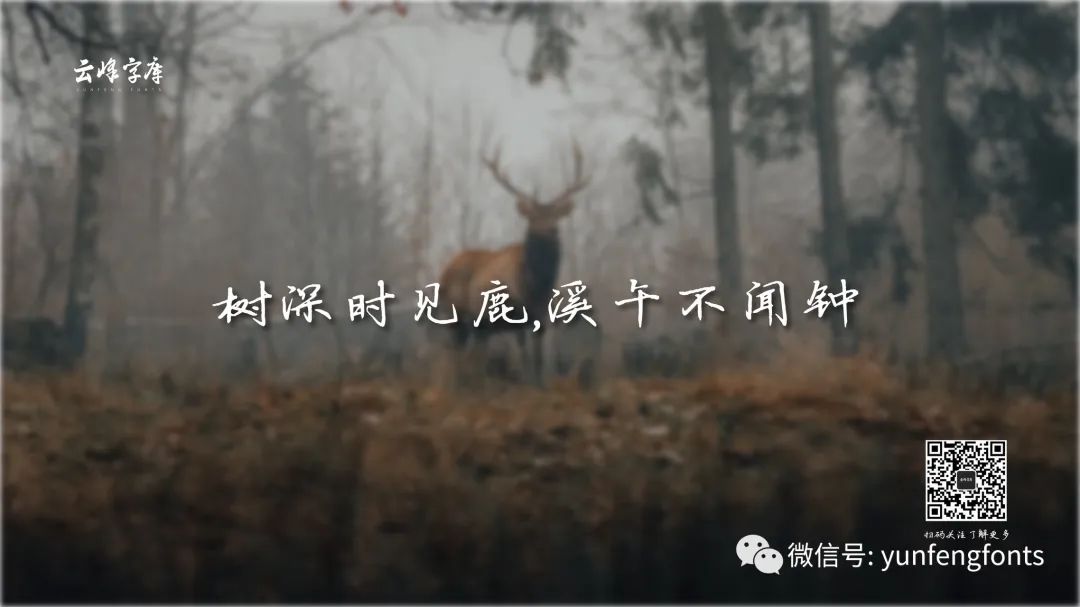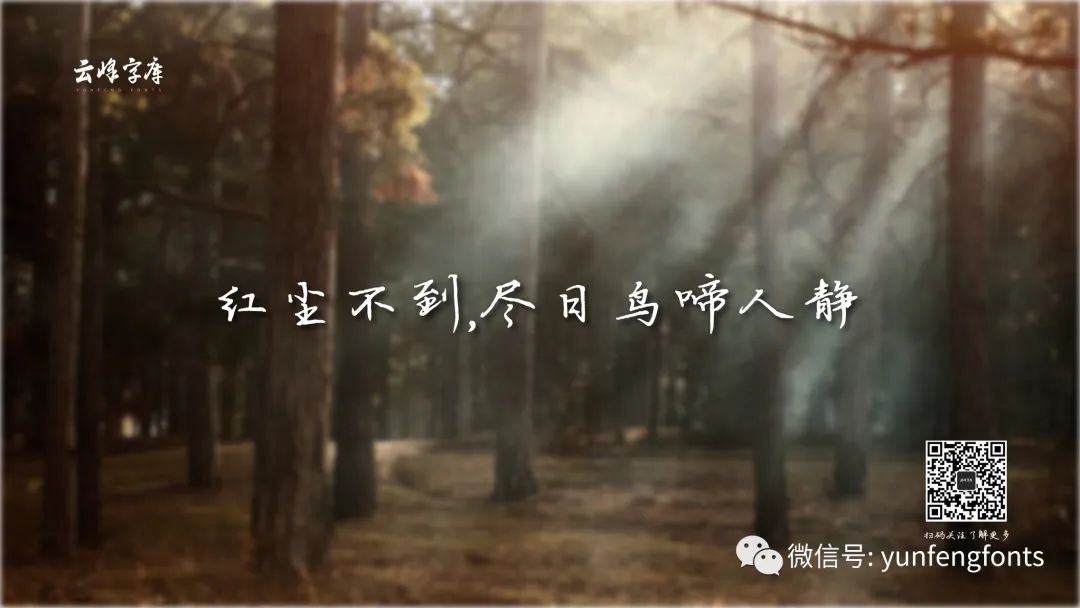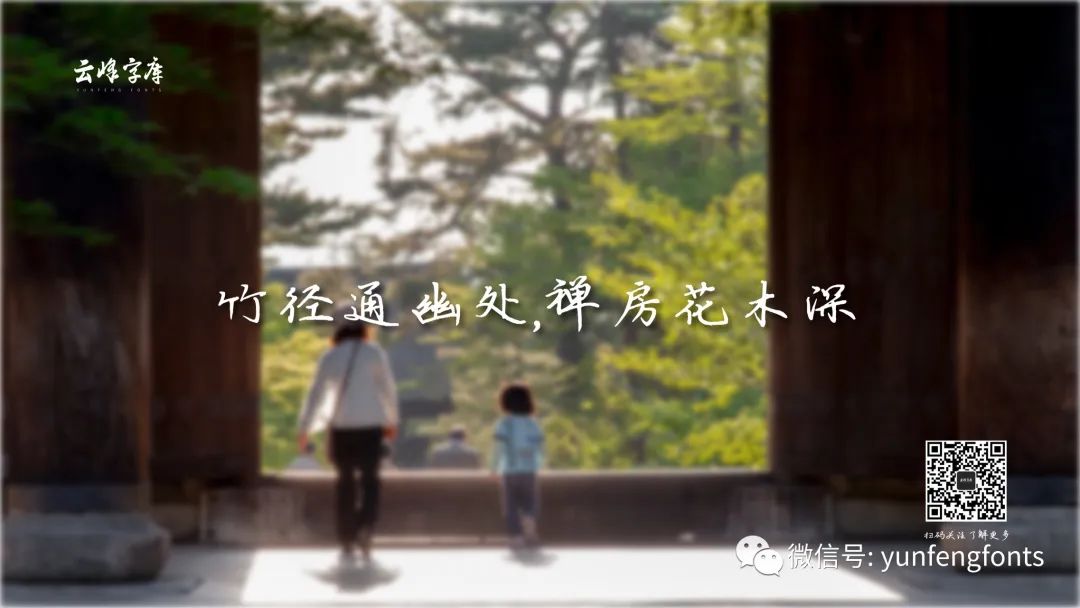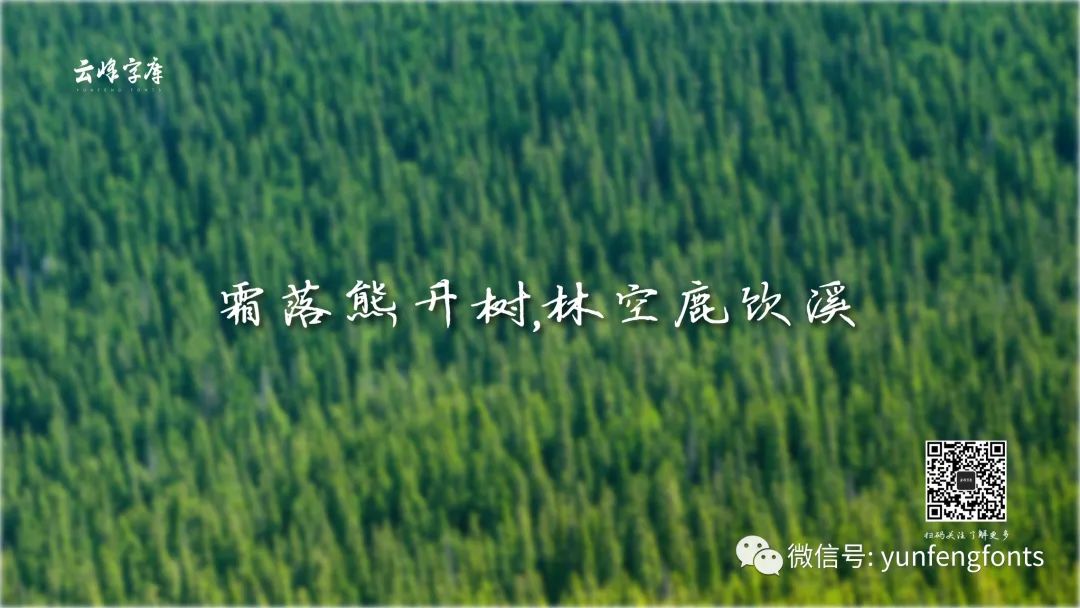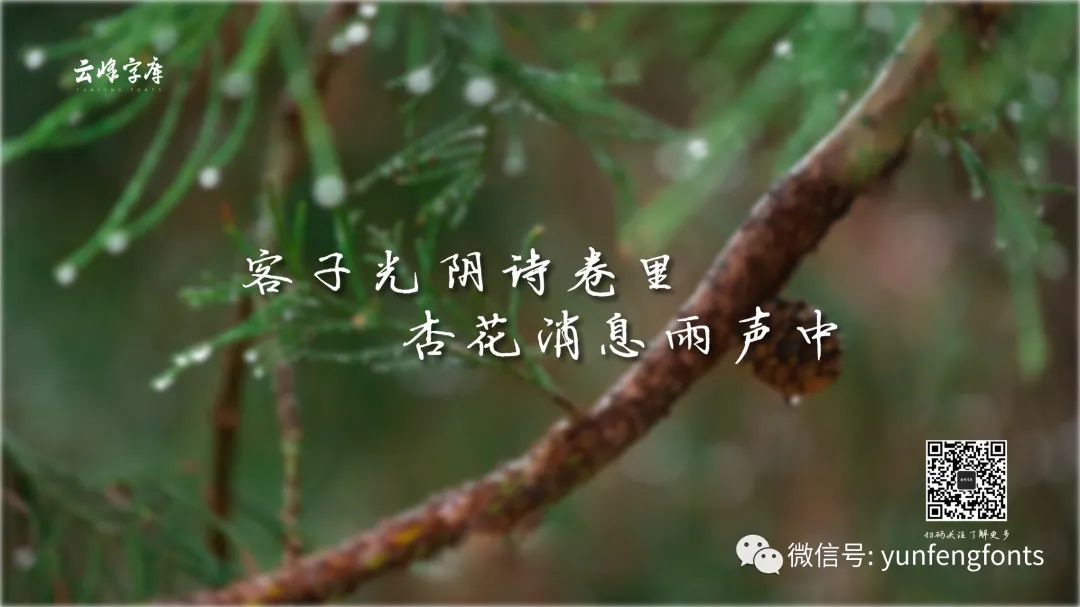
云峰寒蝉体
“云峰寒蝉体”是一款一位美丽少女书写的一款手写字体,这款字很漂亮、耐看,非常适合阅读、排版,可用于海报宣传、书籍排版、装订、文案排版、自媒体视频字幕等,整体阅读性强,是一款好看且实用的硬笔书法字体,欢迎大家使用。在使用过程中如有发现错别字及其它任何问题请反馈到QQ群205961668。
云峰寒蝉体:温润耐看的中文手写硬笔书法字体